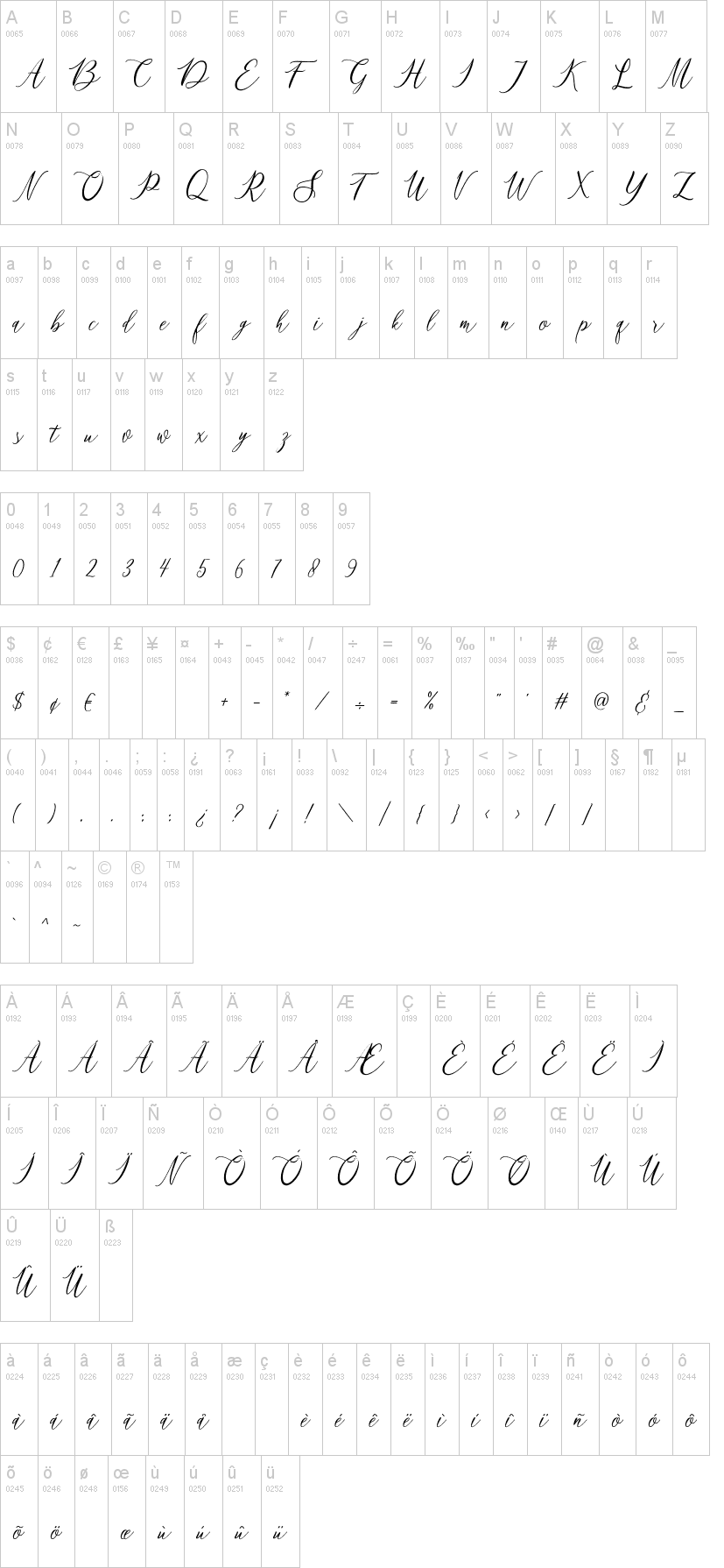
Matania Script
Matania Script 是一种优美的手写字体,其特点在于它的流畅和自然。这种字体由 Matan Stauber 设计,他是一位来自以色列的艺术家和设计师。 Matania Script 字体的设计灵感来自于书法艺术和手写信件。它的线条优美、流畅、自然,让人联想到古老的传统书法。这种字体的设计非常适合用于艺术、设计、手写信件、卡片、海报以及其他类似的项目。 Matania Script 字体包括大写和小写字母、数字、标点符号和特殊字符,使得它非常适合用于各种不同的项目中。此外,该字体提供了多种不同的字重和风格,如常规、粗体、斜体和粗斜体等,以满足不同项目的需要。 总的来说,Matania Script 是一种非常优美、流畅和自然的手写字体,适合用于不同的艺术、设计和文本项目。
Matania Script是一款非常不错的手写艺术字体,具有很好的视觉感,适合于文化类的宣传设计、商业类品牌的广告和产品包装设计以及个性化文字排版等较多场景。
Matania Script字符映射图